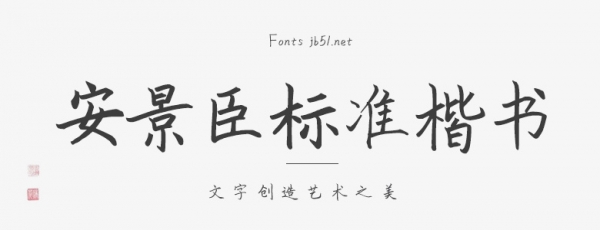
安景臣標(biāo)準(zhǔn)楷書是一款不可多得的楷書字體,系根據(jù)傳統(tǒng)印刷體創(chuàng)新而成,比印刷體靈活,富有生氣,筆畫符合現(xiàn)代寫字規(guī)范,同時有歐體風(fēng)格,具有傳統(tǒng)書法美。廣泛應(yīng)用于:字帖出版、廣告設(shè)計、正文印刷、包裝裝潢等,對普及規(guī)范漢字意義重大。